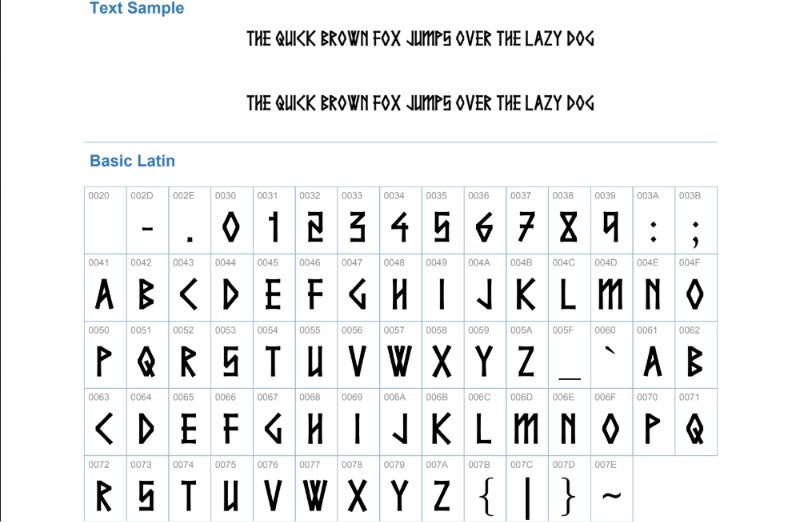
A Noruega está de volta à Copa do Mundo após 28 anos de ausência, e a estreia no Mundial 2026 vem com um presente para os fãs de design e futebol: uma tipografia que é puro DNA viking.
Desenvolvida pela Nike, a nova fonte oficial da seleção norueguesa foi apresentada durante um amistoso contra a Holanda.Inspirada nas runas nórdicas tradicionais (Elder Futhark),a tipografia carrega a força da mitologia escandinava diretamente para os gramados.Não à toa, o uniforme da Noruega foi eleito o mais bonito da Copa.
Detalhes técnicos da fonte
- Diferencial: glifo com o escudo da NFF (Shift + “–”)
Estilo visual da tipografia
A fonte foge do convencional. Cada caractere é construído com traços angulares, cortes diagonais afiados e formas geométricas que remetem à era viking.Os números, em especial, chamam atenção: traços ousados e quebras angulares criam um visual moderno e agressivo.
Diferente da versão de 2024 — que foi proibida por ser complexa demais e ilegível em campo —a tipografia de 2026 foi simplificada para garantir legibilidade à distância, tanto nas arquibancadas quanto nas transmissões de TV.A fonte pesada mantém presença em qualquer escala, do número nas costas da camisa a posts em redes sociais.
Aplicação no uniforme
Home (titular): A fonte rúnica estampa os nomes e números na clássica camisa vermelha, que traz a cruz azul-marinho contornada em branco sobre a bandeira.
Away (reserva): A versão mantém o DNA rúnico, mas ganha um tom mais agressivo e sombrio sobre o fundo preto do uniforme all black.